簡體中文
此簡體中文字體隨 Mac OS 8(1997 年)發佈而發佈。由“上海伊卡罗丝电脑文字有限公司”(見此文)製作。不過自從我用 Mac 開始(OS X 10.7)四款字體僅有兩款(黑體和楷體)保留了,一直保留到現在。如果你看電視裏頭“创”字寫成
,那一定就是用 Mac 自帶的 Hei 了。
据此串言,這些字體的一個版本涵於 WPS 97 之中,似乎并未附帶點陣。
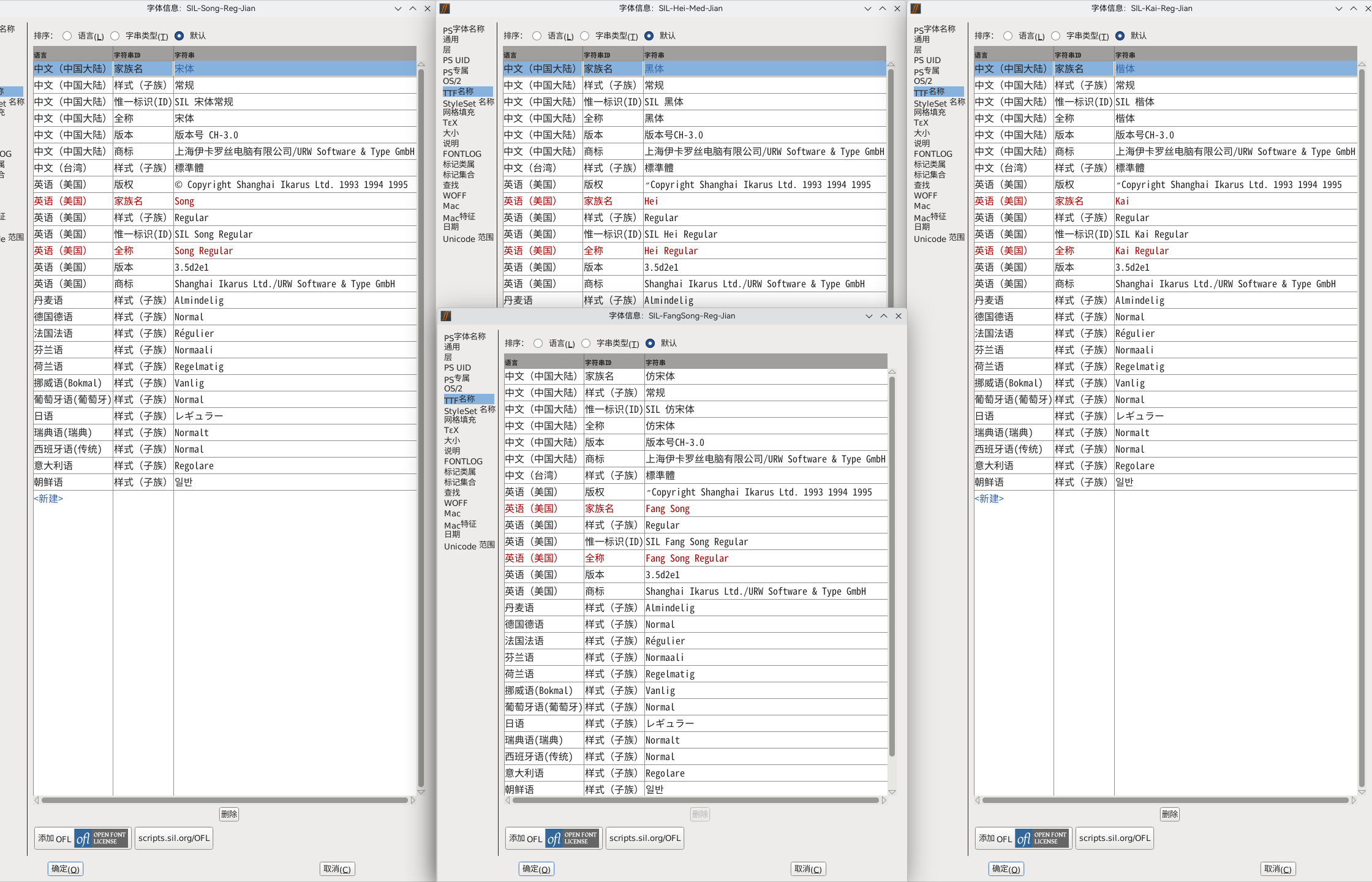
附帶點陣
9px 時,四款字體都附帶同一款點陣(西文不同)。
個人評價:這可能是上世紀唯一一個 9px 的簡中點陣了。
12px 時有兩個不同的情況。宋體、黑體用的是一個點陣,而楷體及仿宋體的點陣卻不一樣。風格上後者就像前者被機械太高,但事實并非如此;某些字還是調了的。
個人評價:可愛捏
16px 的時候,每款字體都有屬於它獨特的點陣了。宋體屬於國標、其他三個雖然個人覺得不好看,但值得説一説。(反正比直接矢量轉強)
個人評價:原創點陣裏頭,仿宋好看、楷體一般、黑體真的感覺不太行…
編輯:又到了我最喜歡的平行眼環節。
原來黑體的大部分字形是拿原先的點陣去襯綫化的啊。我説怎麽那麽爛…
24px 也是一樣。
個人評價:同上,但可惜黑體細看起來會變得更醜了…
Beijing 字體
其實就是 Song 去掉了矢量字部分。另外加上了 10px 點陣,其實就是處理過的 9px 點陣。